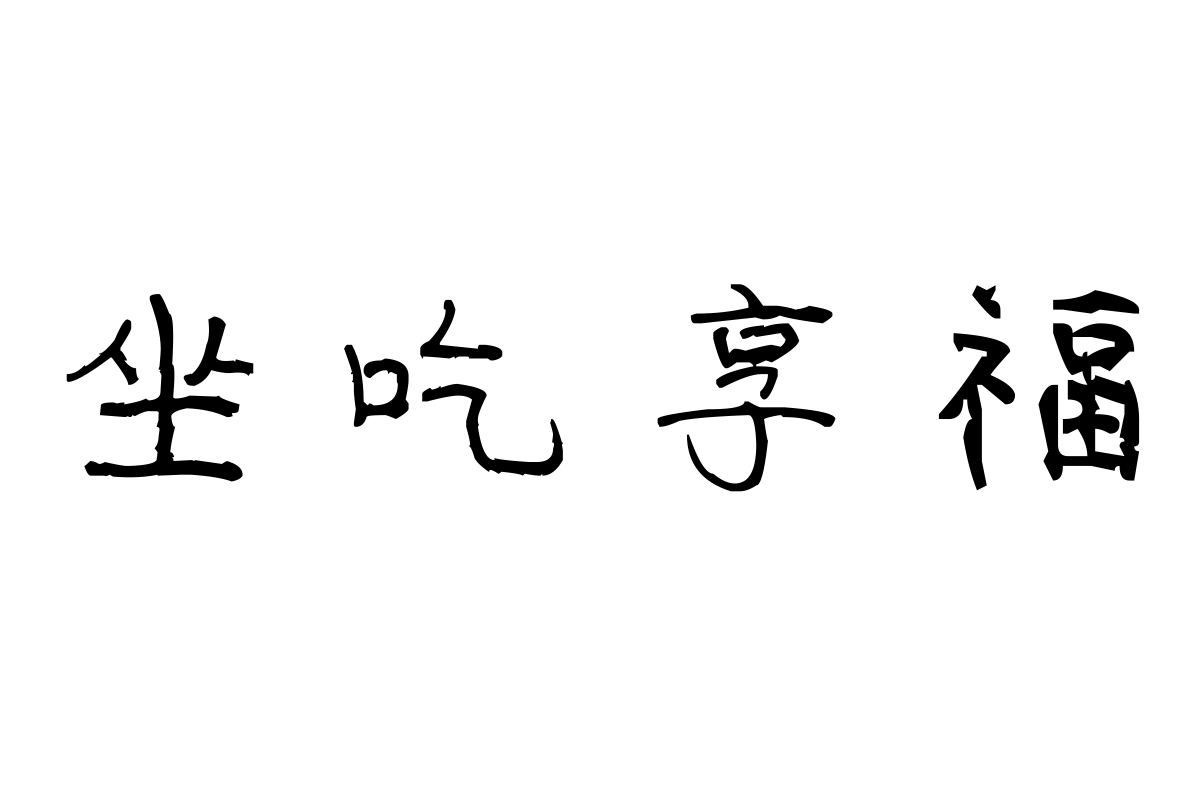
汉呈一见钟情字体是一种具有现代感的中文书法字体,它的特点是简洁、流畅、易于阅读。这种字体的设计灵感来源于中国传统的书法艺术,但又融入了现代设计元素,使得它在视觉上既具有传统韵味,又不失现代时尚感。
汉呈一见钟情字体的特点如下:
1. 字形结构:该字体的字形结构紧凑,线条流畅,笔画粗细适中,给人一种简洁明快的感觉。
2. 风格特点:汉呈一见钟情字体的风格独特,既有传统的韵味,又有现代的时尚感。它的线条柔和而有力,笔画圆润而富有弹性,整体呈现出一种优雅而大气的美感。
3. 适应性:这种字体适用于各种场合,无论是正式的商业文档还是轻松的日常书写,都能展现出其独特的魅力。同时,它也能很好地融入各种设计元素,为设计作品增添一份独特的个性。
4. 易读性:汉呈一见钟情字体的笔画清晰,字形规整,易于阅读和识别。这使得它在各种应用场景中都能保持高效和准确的表现。
总之,汉呈一见钟情字体以其独特的设计风格和易读性,成为了一种受欢迎的中文字体。它不仅能够吸引人们的注意力,还能提升设计作品的整体品质,使人们在视觉上得到愉悦的体验。